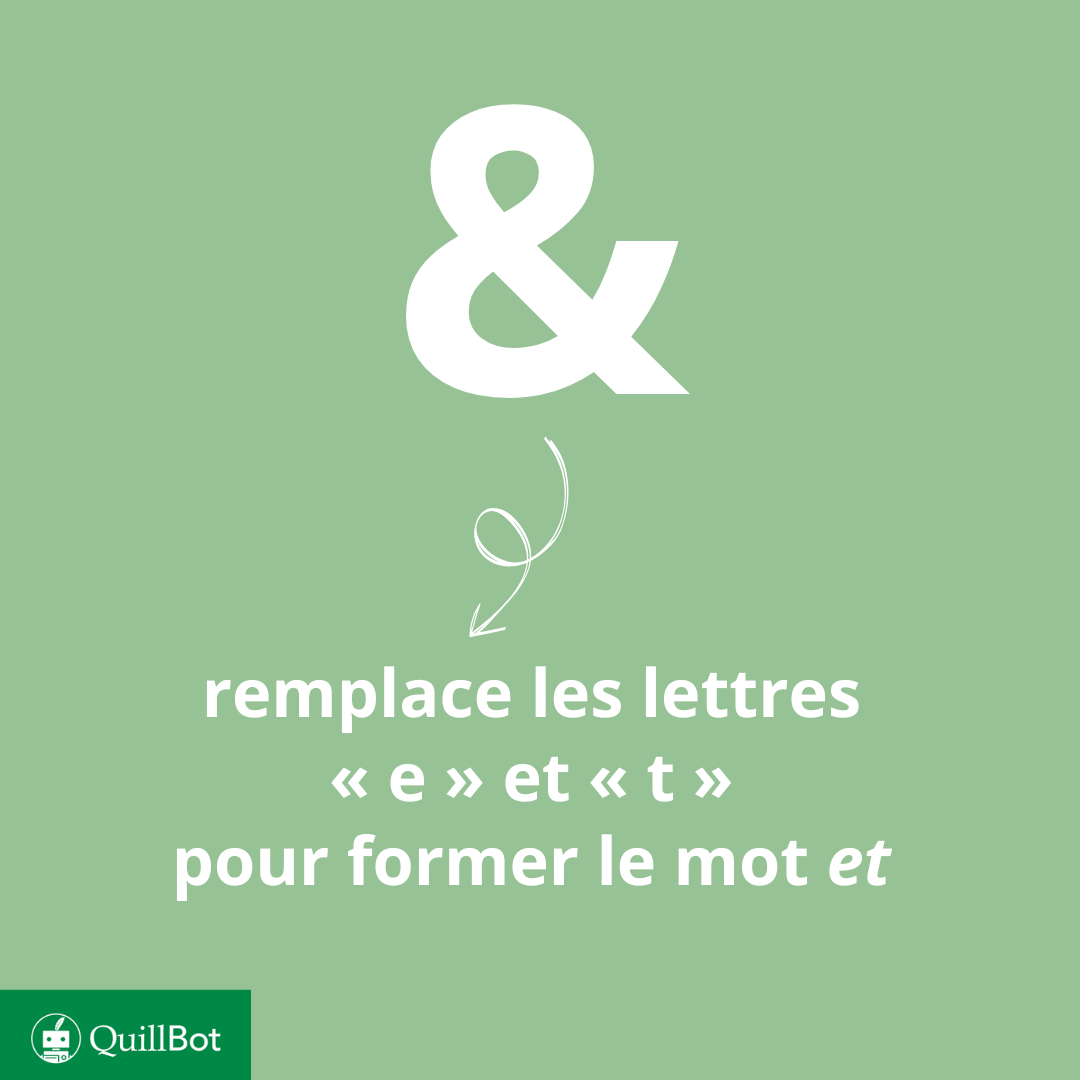
Es-per-lu quoi ? Si le mot esperluette est insolite, son symbole, lui, est très commun et connu de tous.
Symbole typographique (&) signifiant et, utilisé pour son gain de place.
Artifice graphique, l’esperluette et sa ligature remportent haut la main la palme de la longévité parmi les signes typographiques.
Des moines copistes à l’ère du numérique, elle témoigne surtout de l’évolution des langues indo-européennes à travers les siècles. Une graphie sinueuse à l’image de son odyssée et de ses mille & une vies…
Esperluette : définition
L’esperluette, aussi orthographiée esperluète, est techniquement un logogramme, un dessin qui remplace un mot, une suite de lettres ou un son.
Mot féminin, une esperluette remplace, en français, les lettres « e » et « t », soit la suite « et », ainsi que le son formé par ces deux lettres : [e] en alphabet phonétique international.
Esperluette et ligature
Graphiquement, le dessin de l’esperluette représente une ligature, le nœud qui permet d’accoler les lettres « e » et « t ».
Le mot nœud est la définition même de la ligature : les lettres « o » et « e » de nœud sont véritablement nouées, reliées l’une à l’autre par un lien graphique très étroit.
Historiquement, la ligature est employée pour son gain de place. En liant ainsi les lettres, les scribes économisent un matériau rare et cher : le papier.
Avant l’avènement de l’imprimerie, les moines copistes sont chargés de recopier les manuscrits à la main. De fait, ils font grand usage de ce type d’abréviations pour gagner du temps et augmenter leur productivité.
L’esperluette n’abrégeant que deux lettres, sa fonction abréviative semble surfaite. En réalité, son rôle est nettement plus esthétique que pratique. Cette tendance artistique, suivie par les scripteurs anglophones et germanophones, s’impose d’ailleurs dans toute l’Europe médiévale.
De ligature esthétique à artifice typographique, l’esperluette est devenue, au fil des siècles, un véritable logogramme multilingue qui se prononce différemment selon la langue utilisée : et en français, y en espagnol, and en anglais, ou encore und, en allemand.
L’esperluette s’emploie ainsi en lieu et place de la conjonction de coordination et. Dans les textes plus anciens, elle apparait également sous la forme &c, abréviation de la locution latine et cetera, notre etc. moderne.
Cette substitution phonétique, aujourd’hui disparue, est très présente dans les Serments de Strasbourg, un des plus anciens textes de langue romane. Le son [e], qu’il soit un mot entier ou une des syllabes d’un mot, y est remplacé par l’esperluette (par exemple, faire au subjonctif, prononcé fazet, est écrit faz&).
Du reste, l’esperluette s’est parfaitement adaptée à l’ère moderne : elle est partie intégrante des langages de programmation, notamment XML et HTML, sous l’entité de caractères & qui reproduit son symbole graphique (&).
L’esperluette « numérique » se retrouve sur et derrière nos écrans : dans la charte graphique d’une entreprise, le logo d’une marque ou le code source d’un site.
Omniprésente, elle n’en demeure pas moins un symbole, et non une lettre ; elle n’a pas de touche dédiée sur un clavier alphabétique.
Si vous disposez d’un clavier alphanumérique, la touche 7 devrait produire l’esperluette. Si ce n’était pas le cas, assurez-vous d’appuyer simultanément sur les touches shift et 7.
Le symbole & peut également s’obtenir en tapant une combinaison de touches : alt, suivi des chiffres 3 et 8 sur le clavier numérique (alt+38).
Esperluette : histoire & fonction
Si ce logogramme possède de nombreuses dénominations (éperluette, perluète, « et » commercial ou encore « et » américain), tous ces noms désignent pourtant le même symbole. Toutefois, son qualificatif d’américain est très largement usurpé…
Il est vrai qu’elle se retrouve dans de nombreuses marques d’influence anglo-saxonne. Que ce soit l’industrie vestimentaire (H&M, Marks & Spencer), alimentaire (M&M’s, Ben&Jerry’s) ou cosmétique (Head & Shoulders, Johnson & Johnson), l’esperluette est très productive chez nos voisins anglophones.
Elle n’est cependant pas l’apanage de l’anglais : la revue Sciences & Vie ou le magasin Nature & Découvertes, pour ne citer qu’eux, sont des exemples bien français. De plus, l’utilisation de l’esperluette dans les raisons sociales — le nom des entreprises — n’a rien de moderne.
Dès le XIXe siècle, elle a, dans toute l’Europe, lié des patronymes, des prénoms, des initiales, et même des mots explicitant certaines relations familiales et commerciales, comme Fils, Frère, Associé ou Cie, abréviation de compagnie.
C’est d’ailleurs cette fonction de dénomination juridique des entreprises qui lui a valu l’étrange qualificatif de et commercial. Et si ce nom n’est pas très usuel, il a le mérite de faire honneur à sa fonction essentielle : lier les lettres et les êtres…